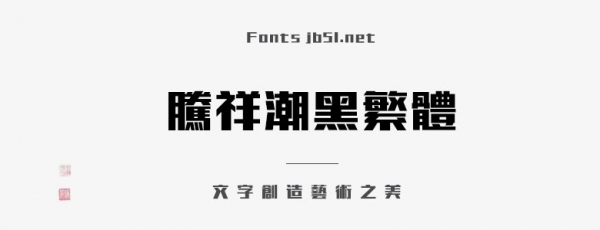
騰祥潮黑繁體是一款不錯(cuò)的藝術(shù)字體,由騰祥字庫(kù)出品,字形結(jié)構(gòu)扁方、端莊,橫豎筆畫(huà)粗細(xì)比例適度、豎筆粗壯有力,布白均勻、行文貫通,適合應(yīng)用于藝術(shù)設(shè)計(jì)、平面宣傳設(shè)計(jì)、網(wǎng)頁(yè)設(shè)計(jì),書(shū)法字帖等領(lǐng)域,需要的朋友可以前來(lái)本站下載。
騰祥潮黑字體是騰祥公司自主精心設(shè)計(jì)開(kāi)發(fā)的美術(shù)黑體。字形結(jié)構(gòu)扁方、端莊,橫豎筆畫(huà)粗細(xì)比例適度、豎筆粗壯有力,布白均勻、行文貫通。字體風(fēng)格:字形飽滿富于張力;筆畫(huà)硬朗簡(jiǎn)潔表現(xiàn)清晰;為了起到裝飾效果左右結(jié)構(gòu)字形在不影響閱讀的前提下,部分點(diǎn)和提、撇和點(diǎn)做連筆畫(huà)處理,更好的展現(xiàn)出字形的連貫性和整體感。潮黑筆畫(huà)簡(jiǎn)潔有力細(xì)微處變換靈動(dòng),即實(shí)用又富有裝飾效果。潮黑為粗黑一款,為了調(diào)整黑白空間在筆畫(huà)交叉處特別做了墨跡處理,使整體筆畫(huà)看起來(lái)既粗壯醒目又清晰易讀。適合標(biāo)題用字,可用于印刷出版、包裝設(shè)計(jì)、廣告設(shè)計(jì)、網(wǎng)頁(yè)設(shè)計(jì)等。